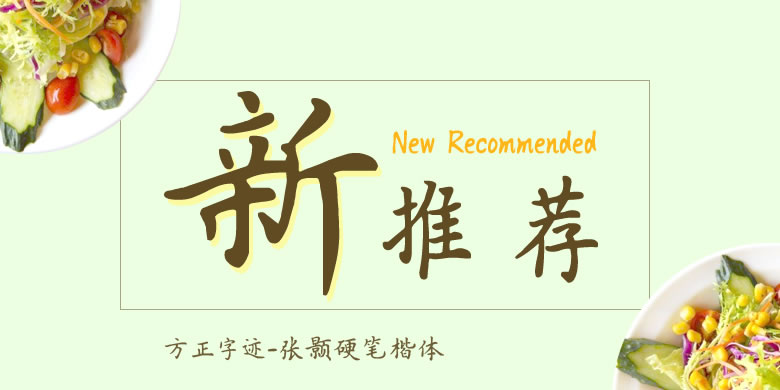
方正字迹-张颢硬笔楷体
品牌:方正字迹设计师:张颢发行时间:2009字库编码:大陆简体(GB2312-80)、大陆繁体(GB12345-90)分类:常规书写·硬笔
方正字迹-张颢硬笔楷体由硬笔书法家张颢先生创作。这款字体的笔画比通常的硬笔字体略粗,字形大小的变化富有节奏。其风格中和大方,适用于现代诗歌、短文的排版,以及文化、商业类品牌的广告语设计。